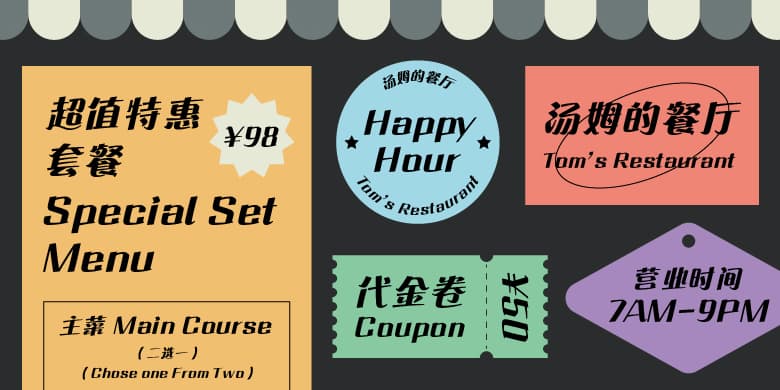
品牌:方正字库设计师:郭炳权发行时间:2020字库编码:大陆简体(GB2312-80)、简繁扩展(GBK)分类:创意字体字体属性:精品字
方正流畅体家族:流畅体是用斜体形式表达,充满动感和速度,通过连笔的设计,增强轻松愉快自由自在的感受。
适合汽车、航空、旅游、运动等相关行业和快速消费品的各种宣传等。